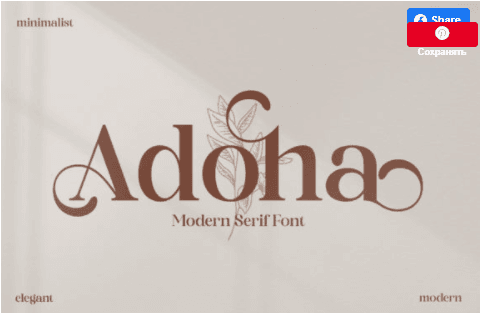
Adoha Font
С гордостью представляем шрифт Adoha.
Современный и классический шрифт с засечками, отличающийся собственным уникальным стилем и современным внешним видом.
Этот шрифт идеально подходит для элегантного и роскошного логотипа, дизайна названия книги или фильма, модного бренда, журнала, одежды, надписей, цитат и многого другого.